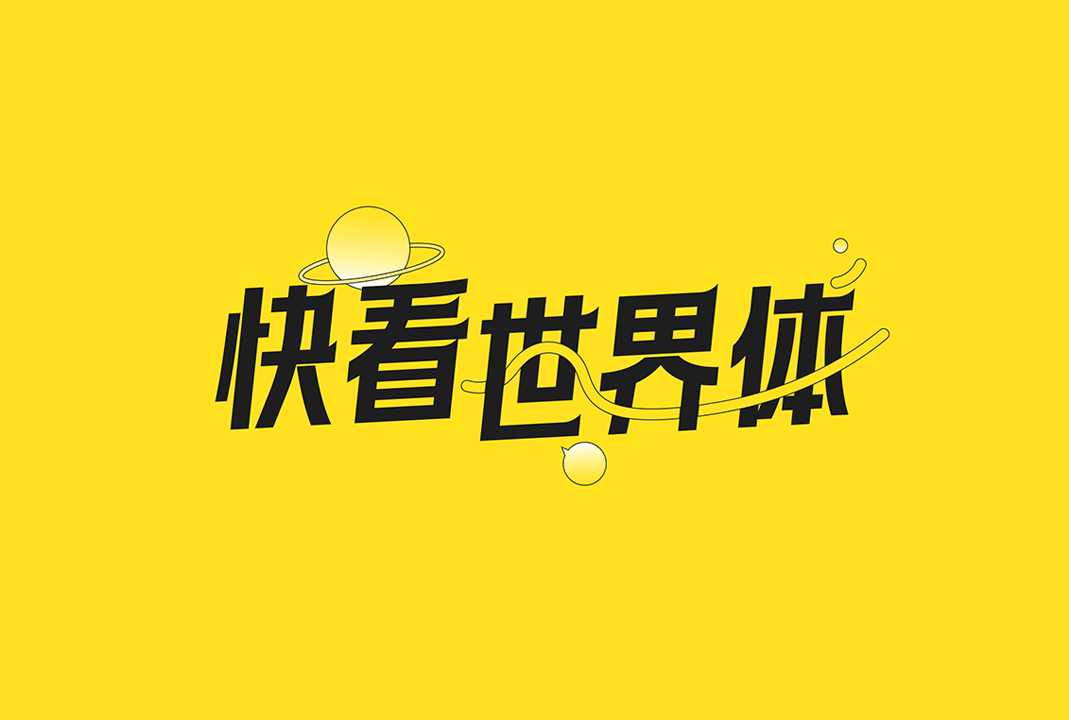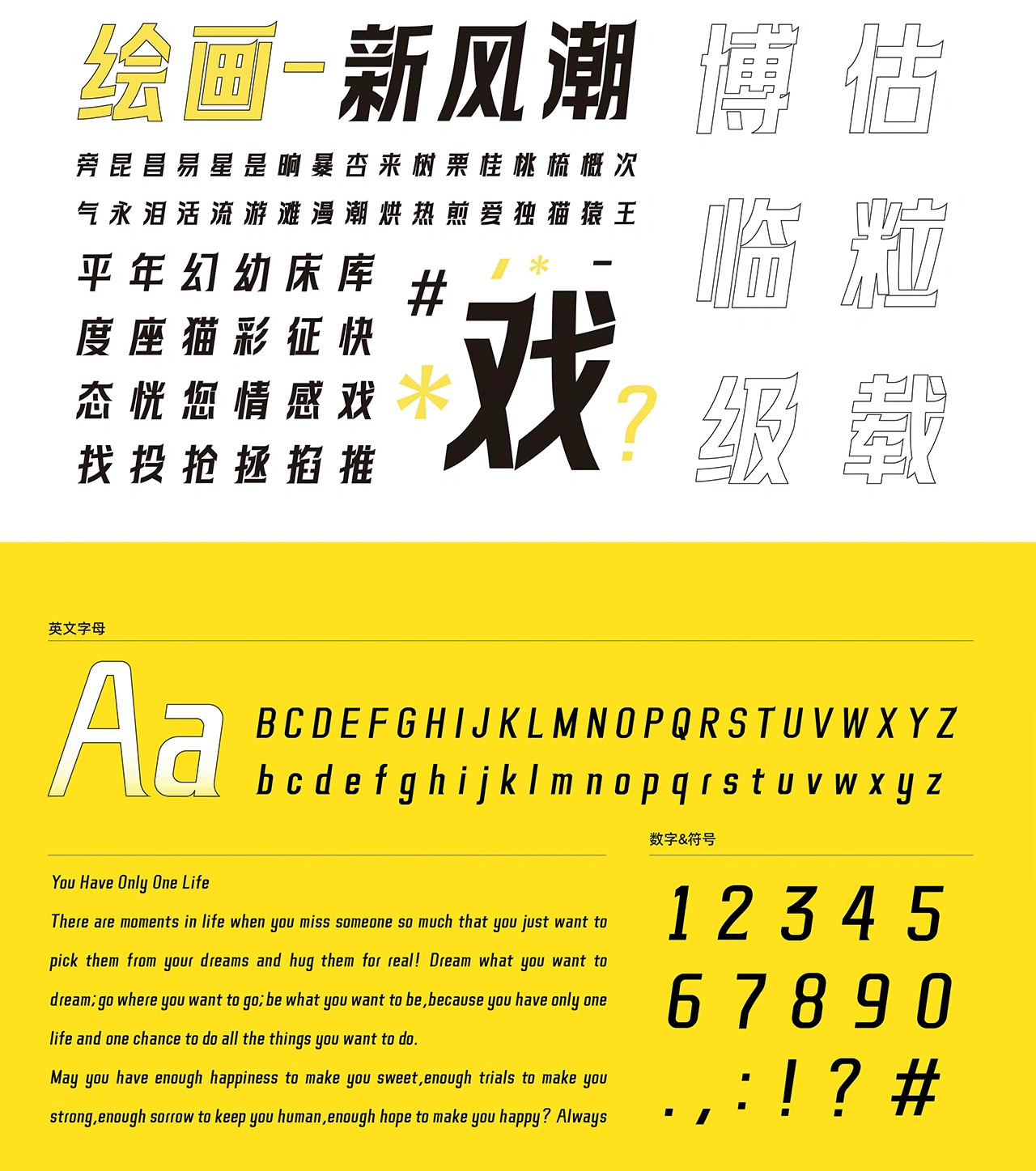
快看世界体 | 中文免费字体_免费商用字体下载
快看世界体由快看 KKDC(快看设计中心)出品,该字体特点末端尖角,中宫外扩、字面瘦长、倾斜 8 度;包含 3501 个字,以漫画中的对话框元素为起点,融入快看 ACGN 文化,年轻潮流,大胆有态度。
现应用于快看品牌营销、漫展、内部企业文化宣传、客户端等场景。